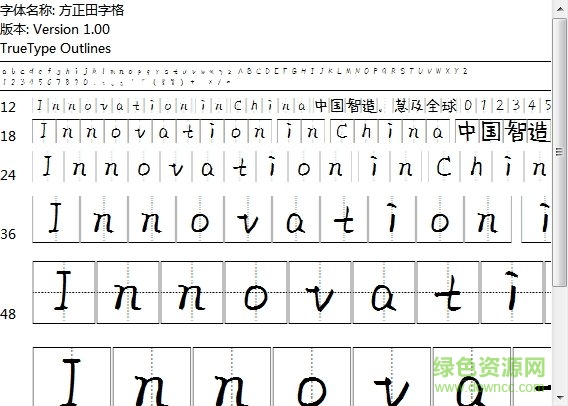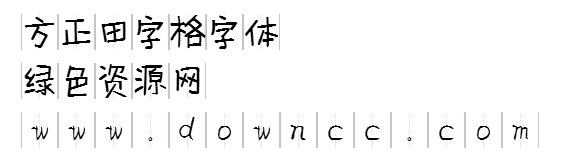
田字格字體是方正字體推出的一款十分獨(dú)特的手寫字體,在文字的周圍增加了獨(dú)特的田字格圖案,顯得更加q萌,喜歡這種風(fēng)格的朋友就來綠色資源網(wǎng)試試吧!
田字格是一種用于規(guī)范漢字書寫格式的模板,包括四邊框和橫中線、豎中線。是小學(xué)初學(xué)寫字規(guī)范。習(xí)字時(shí)需在田字格中逐漸將漢字寫規(guī)范,能給以后的語文學(xué)習(xí)打下堅(jiān)實(shí)的基礎(chǔ)。
田字格別看只是四個(gè)小格子,其實(shí)每個(gè)格子都大有名堂,每根線、每個(gè)格子,格子中的每個(gè)方位,都有其不同的名稱,熟記田字格、牢記各部分名稱,是初學(xué)書寫重要的前提。認(rèn)識(shí)了“田字格”后,欣賞田字格中的漢字,讓孩子感受到每個(gè)字都有他的位置,而不能胡亂擺放,這是一個(gè)重要的環(huán)節(jié)。左右結(jié)構(gòu),上下結(jié)構(gòu),半包圍結(jié)構(gòu)等等。只有在田字格中逐漸將漢字寫規(guī)范,這樣才能給以后的語文學(xué)習(xí)打下堅(jiān)實(shí)的基礎(chǔ)。